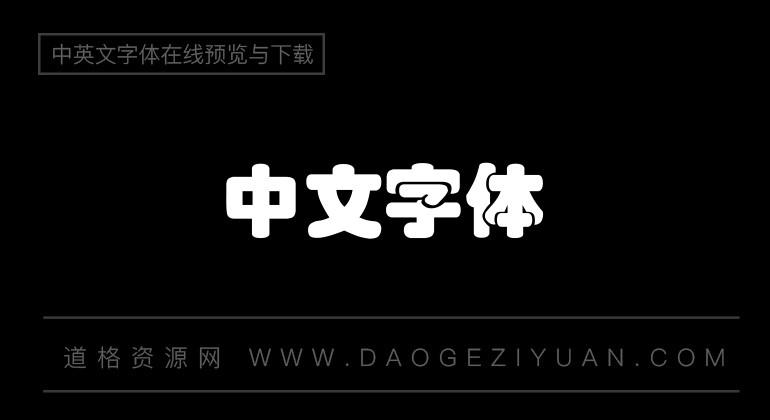
中国龙叠圆体
中国龙叠圆体是一款结合了中国传统文化和现代技术的字体。它将中国传统文化中的龙图案与叠圆体字体结合,形成一种新的、独特的字体风格。它具有浓厚的中国传统文化气息,在视觉上具有很强的表现力,可以用来创造出丰富多彩的文字效果。此外,它还具有良好的可读性,可以满足各种不同的文字需求。
中国龙叠圆体是一款非常不错的手写艺术字体,具有很好的视觉感,适合于文化类的宣传设计、商业类品牌的广告和产品包装设计以及个性化文字排版等较多场景。